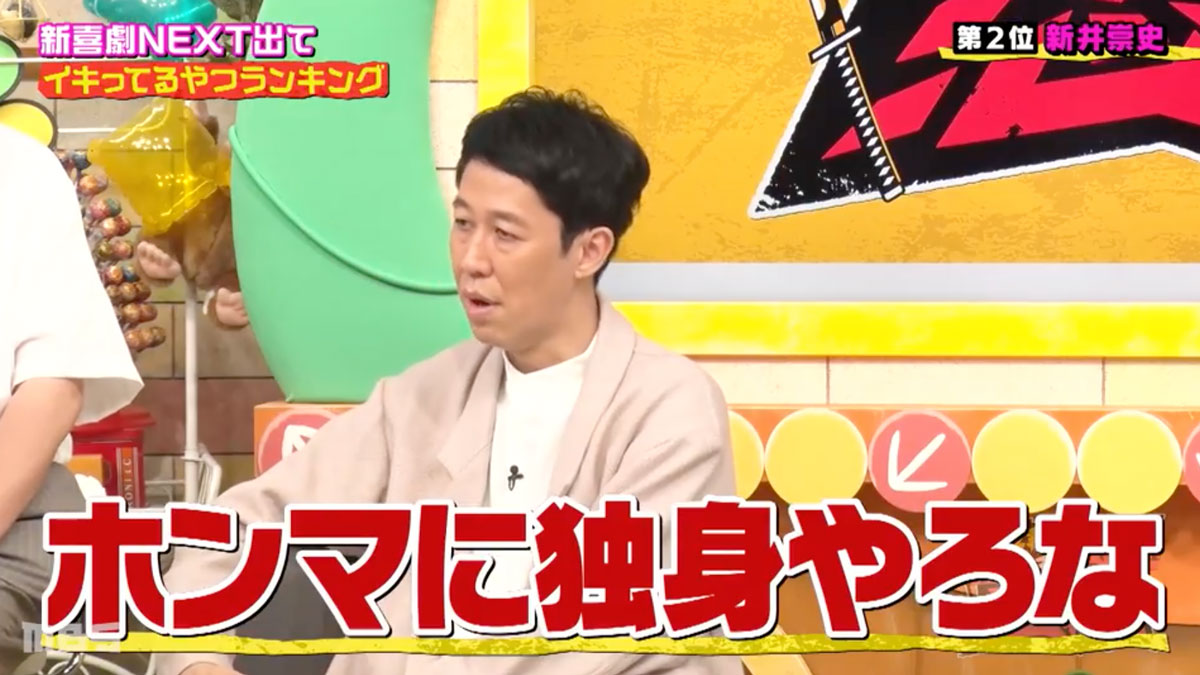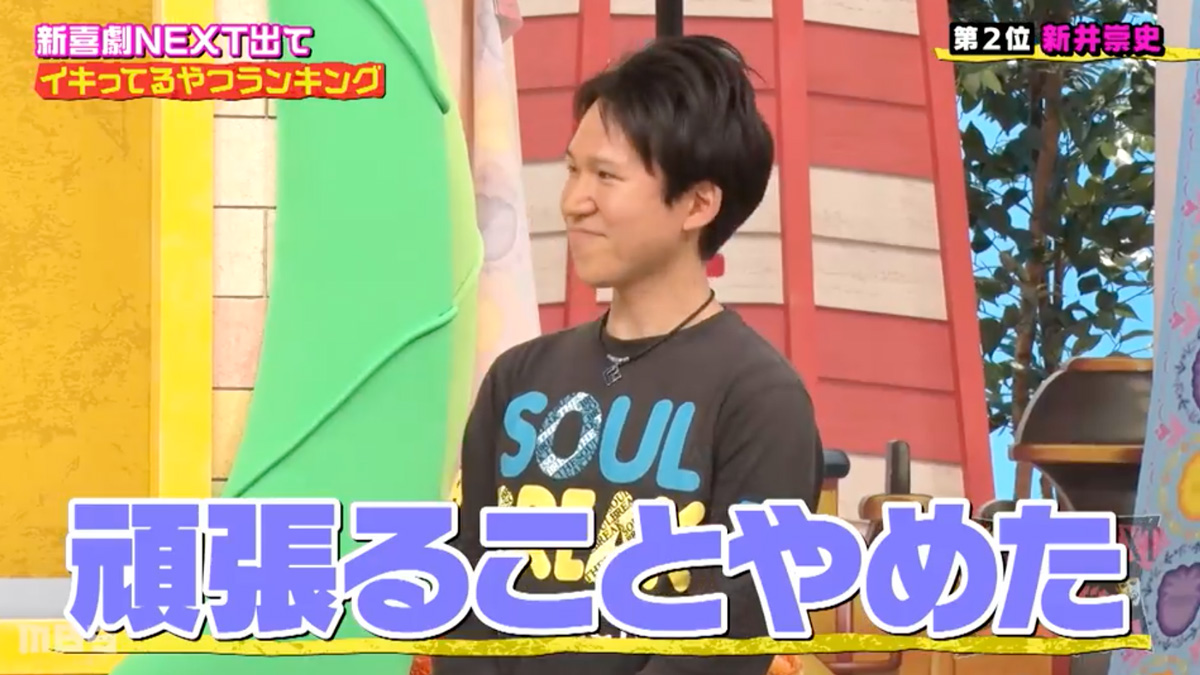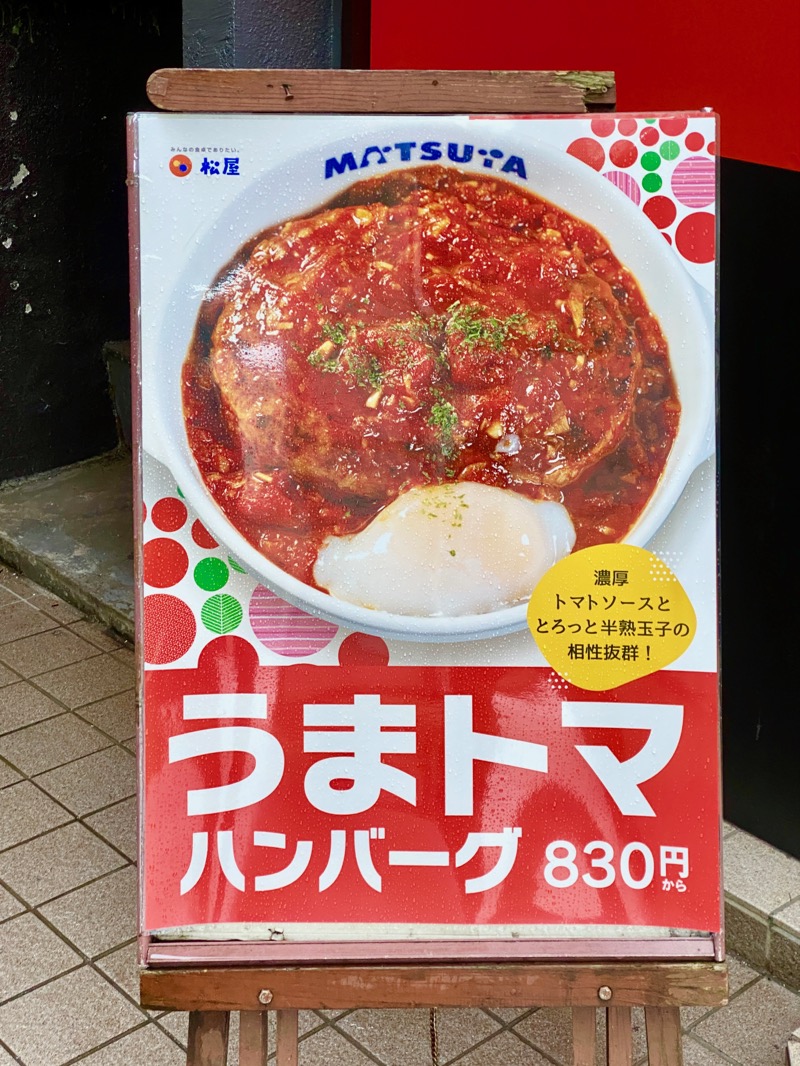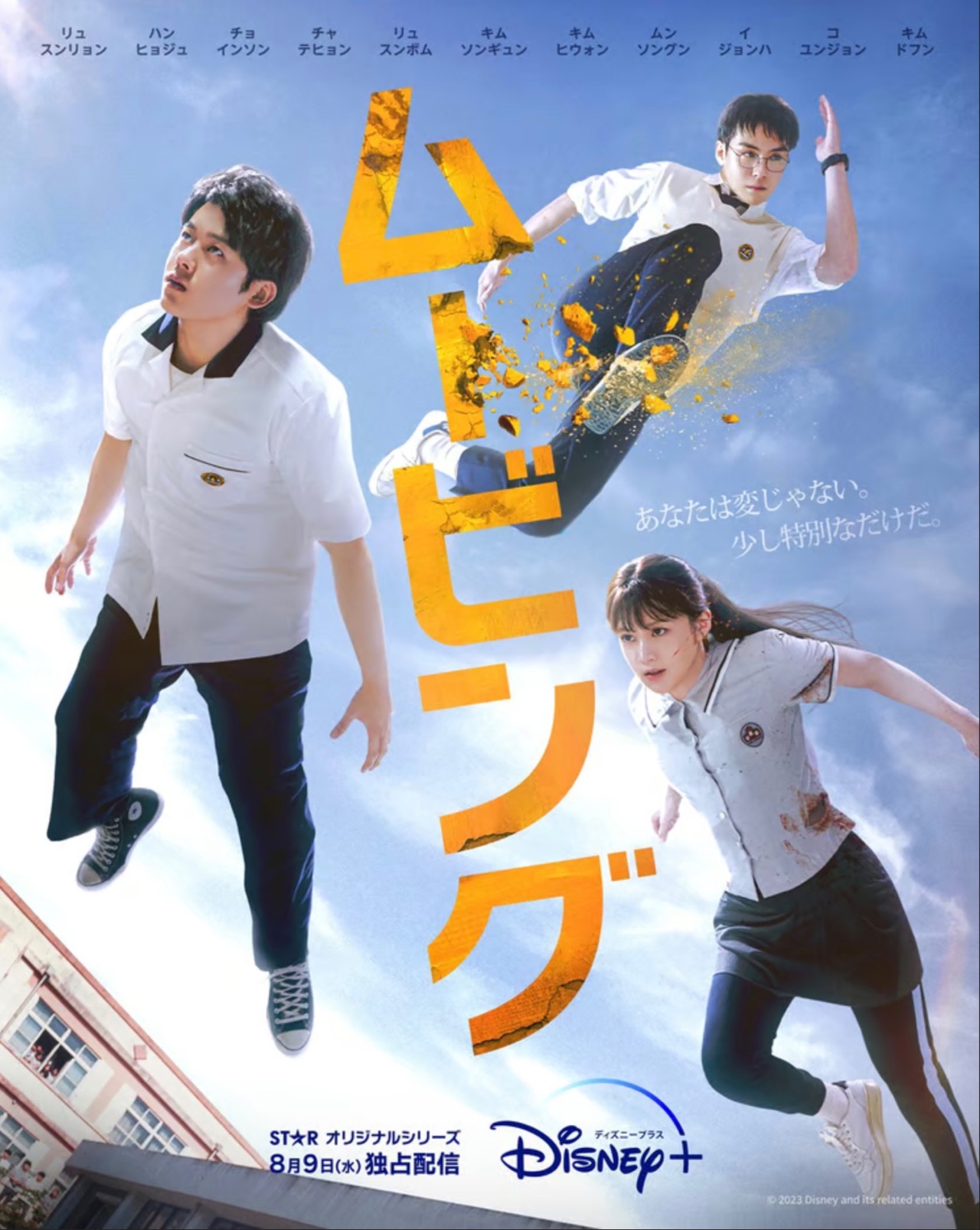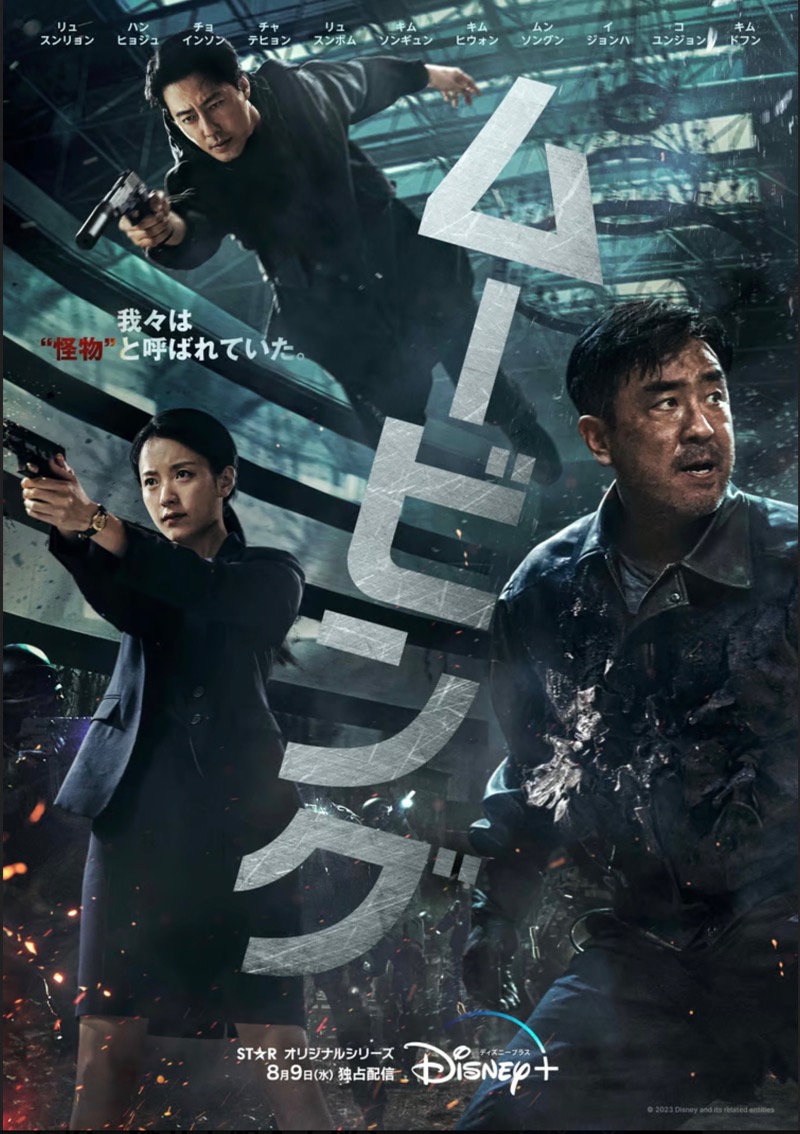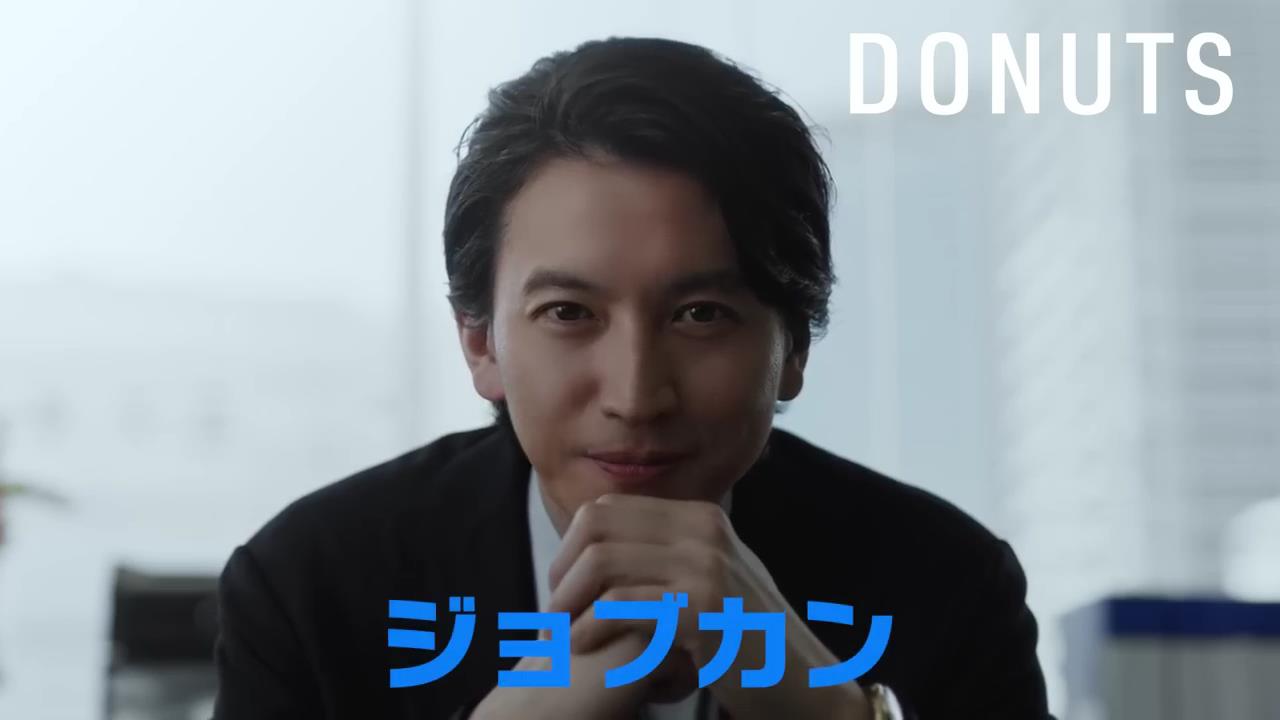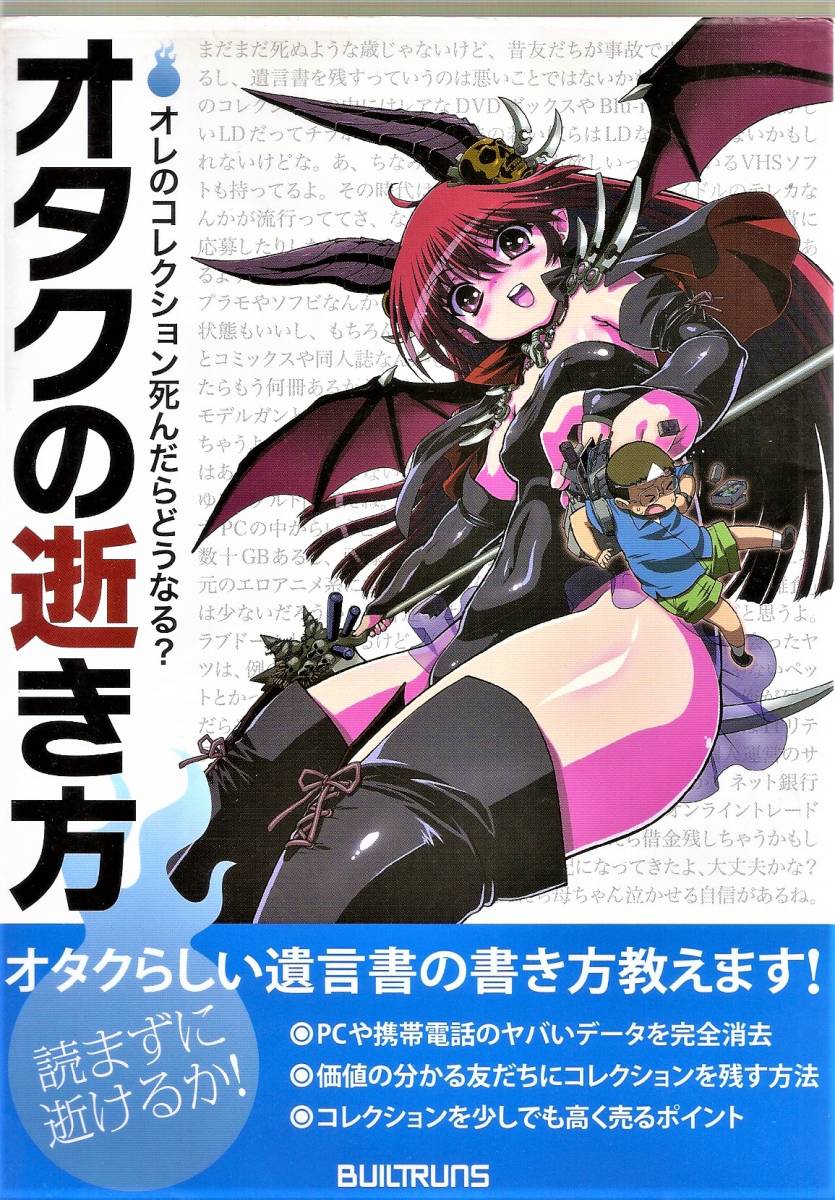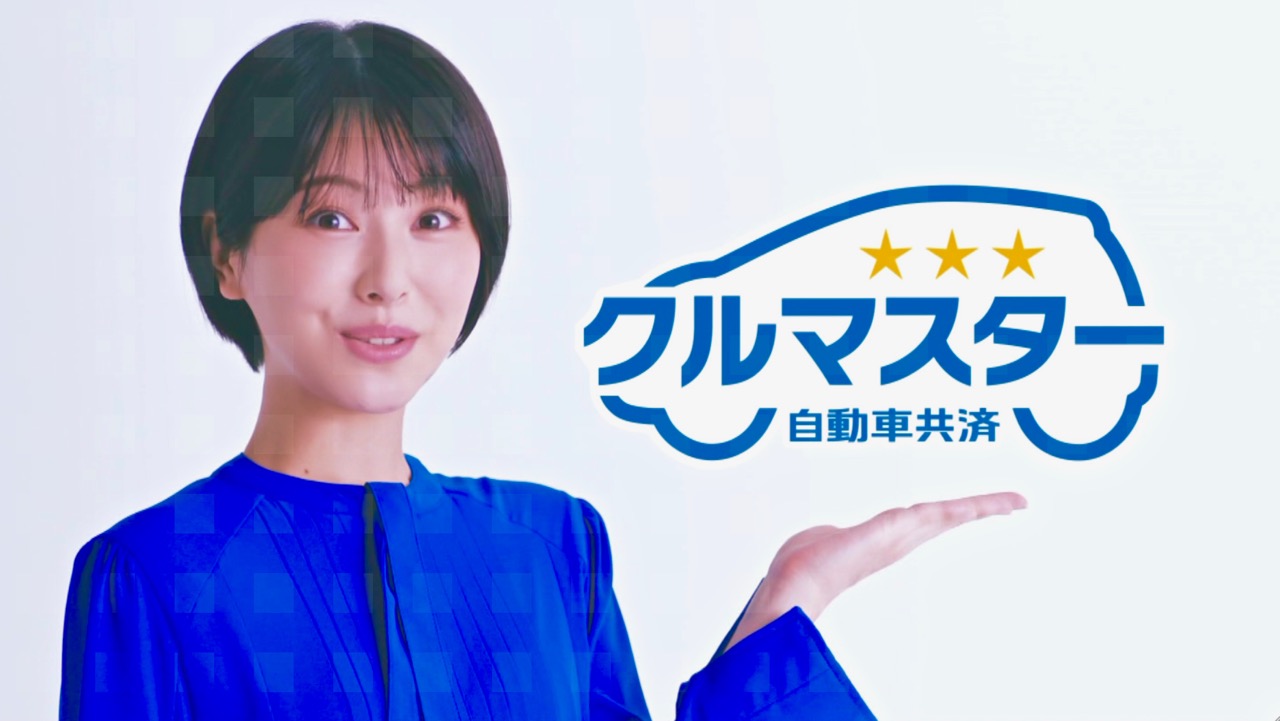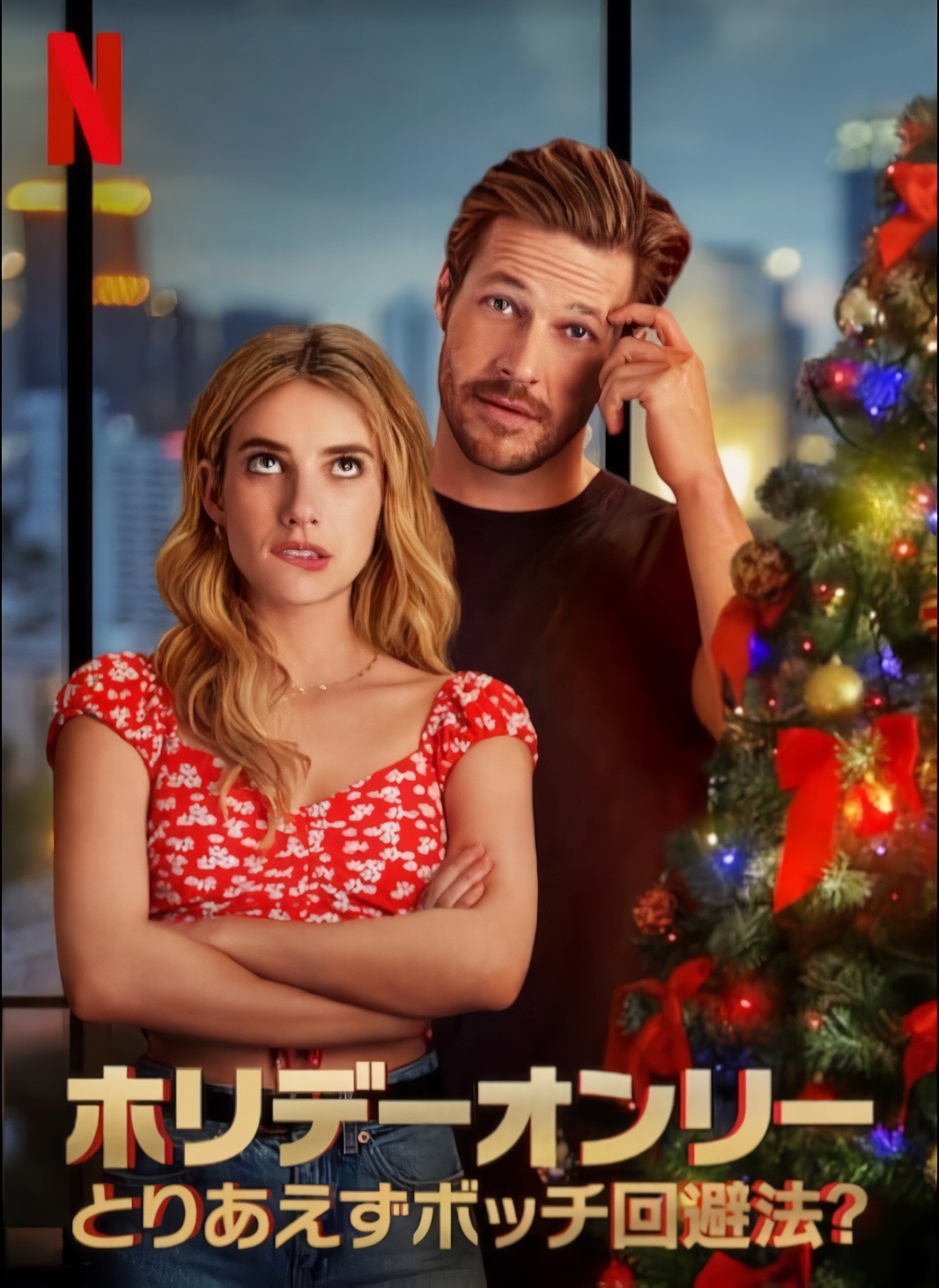
病院で…  さとうゆたか  2024年11月25日(月) 9:04
年に一度の特定検診に行った、近所の病院に貼られていたポスター。
リメイク版「ドラクエ3」  takumi  2024年11月16日(土) 23:35  HP
11月14日にNintendo Switchなどのゲーム機用に発売された、リメイク版の「ドラゴンクエストIII そして伝説へ…」。
ゲーム内のテキストにニタラゴが使われています。
最後にこれも。
大きく使われてる  さとうゆたか  2023年4月15日(土) 8:27
ビル壁面…。
トランクルームのようだ。
これも…。
ルームの前の文字列を見つけました…。
トランクのあとの文字がルームなんだと、なんとか見える。
地下鉄日比谷線の乗客に見えるように描かれた、レンタルスペースの標識だったようです。
やっと「トランクルーム」の文字が揃った〜〜。
地下鉄日比谷線に北千住から乗車して走る車内から撮影。
南千住駅手前の隅田川を渡ってすぐの場所。
昨日、荒川区側の隅田川テラスへ行って撮りました…。
江戸川区にも  さとうゆたか  2024年11月9日(土) 10:08 [修正]
先日、江戸川区を散策した時に見つけた…。
ここでは、太いフォントが使われていたよ。
小学生ドリル  さとうゆたか  2024年10月24日(木) 10:58
ポケモンずかんドリルシリーズ。
これはポスターかな…。
本の表紙  さとうゆたか  2024年9月16日(月) 9:54
書名:はじめてのサーフィン
著者:市東重明
発行:KADOKAWA
マクドナルド  さとうゆたか  2024年8月19日(月) 7:42
この会社の広告には、ず〜〜〜っと前から使われている。
これもか…。
店外に貼られていたポスター。
本の表紙  さとうゆたか  2024年7月25日(木) 15:06
書名:オタマジャクシハンドブック
著者:松井正文 解説/関慎太郎 写真
発行:文一総合出版
県民会館のロゴ  さとうゆたか  2024年7月13日(土) 9:18
ニタラゴルイカ。
すぐに捨てられるチラシとか、すぐに忘れられる広告での使用より、こういう建築物に使われると私の書体が永く残ってウレシイ(撮影者に感謝)。
トーサイクラシックホール岩手(岩手県民会館)。
広告画像  さとうゆたか  2024年6月28日(金) 9:15
昨日から大量に露出している楽天の広告。
「チ」の1画目が、オリジナルとは違う形に加工されている…。